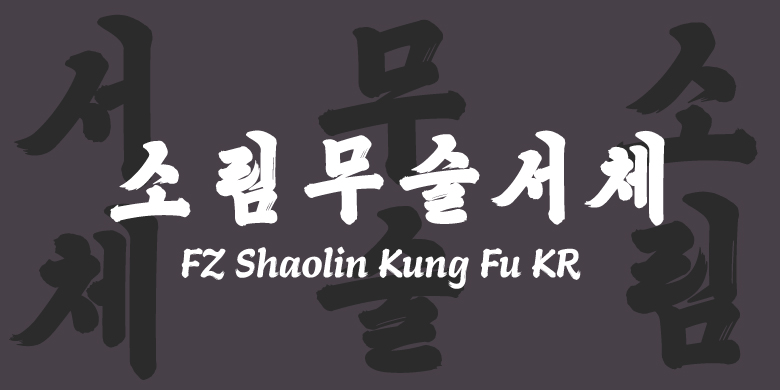
FZ Shaolin Kung Fu KR
방정소림쿵푸체는 소림사의"천애만곡"비에서 유래한 것이다. 글꼴 디자인에서 획의 운필 부분을 매끄러운 곡선으로 디자인화 해서 세련되고 간결하다. 필획의 시작과 끝은 붓글씨의 질감을 복원하는 동시에 비백견사의 요소를 융합시켜 방정소림쿵푸체가 석각의 강건하면서 질박한 성질과 붓글씨의 디테일함과 서정적인 정서도 동시에 가지도록 하였다. 이 서체
는 자형이 웅장하고 강직하며 부드러우며 행서의 행운유수가 있을뿐만 아니라 비각의 듬직하고 견실하여 소림쿵푸의 형상과 완벽하게 융합되었다. 방정소림쿵푸체는 다언어문종의 최대 폰트로서 중문간체, 중문번체, BIG5번체, 일본어, 한국어, 라틴, 그리스, 키릴, 아랍 등 여러 언어를 개발할 계획이다. 서로 다른 언어와 문자, 서로 다른 서사 습관과 심미 전통을 가지고 있으며, 디자인에서 각 언어 문종의 특징을 고루 고려했을 뿐만 아니라 전체 스타일의 통일도 유지했다"고 말했다.
디자이너: 왕문, 진우, 하시양 (라틴 및 소어종)
디자이너: 왕문, 진우, 하시양
글꼴 분류: 일반 쓰기 • 붓